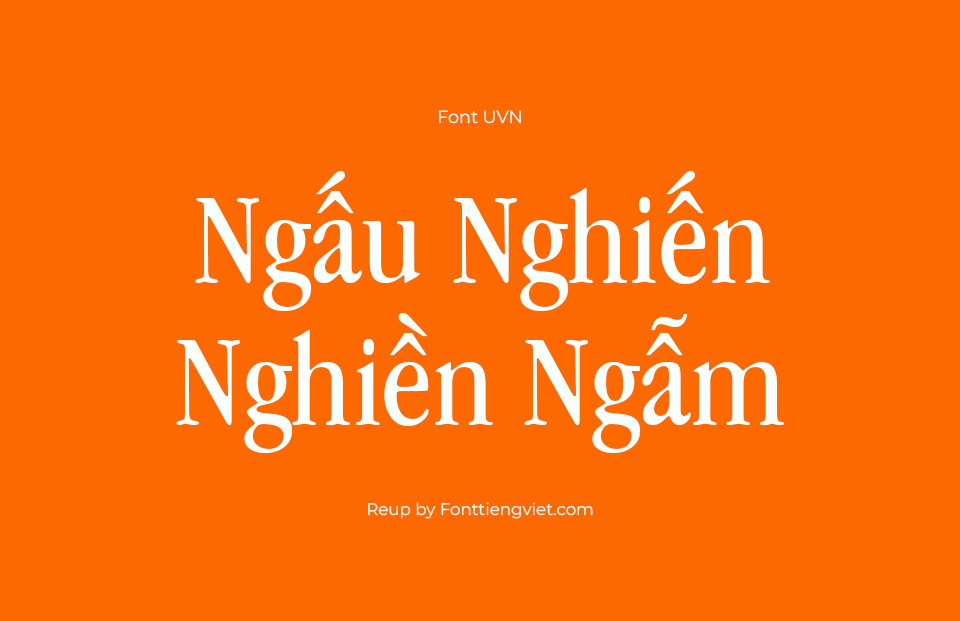
Font Việt Hóa UVN Gia Dinh Hep – Bộ Font Chữ Tuyệt Đẹp Cho Thiết Kế Học Đường
Giới thiệu về Font Việt Hóa UVN Gia Dinh Hep
Trong thế giới đồ họa hiện đại, việc tìm kiếm một bộ Font Chữ phù hợp với văn hóa Việt Nam là điều rất quan trọng. Font Việt Hóa UVN Gia Dinh Hep là một trong những lựa chọn hàng đầu dành cho các bạn học sinh và thầy cô giáo. Đây là phông chữ thuộc bộ UVN nổi tiếng, được tinh chỉnh để hiển thị tiếng Việt một cách hoàn hảo mà không bị lỗi dấu. Với kiểu dáng thanh mảnh và gọn gàng, bộ font này giúp tiết kiệm diện tích trình bày nhưng vẫn giữ được sự tinh tế, trang trọng trong từng nét chữ.
Đặc điểm nổi bật của Font Việt Hóa UVN Gia Dinh Hep
Thiết kế tối ưu cho văn bản dài
Đúng như tên gọi “Gia Dinh Hep”, các ký tự trong bộ font này được thiết kế với chiều ngang hẹp hơn so với các phông chữ truyền thống. Điều này cực kỳ hữu ích khi bạn cần trình bày các đoạn văn bản dài trên báo tường, tờ rơi học tập hoặc các slide thuyết giảng có không gian hạn chế. Font Việt Hóa UVN Gia Dinh Hep giúp nội dung trở nên súc tích, dễ nhìn và không gây cảm giác rối mắt cho người đọc.
Tính ứng dụng cao trong học đường
Phông chữ này mang phong cách cổ điển pha lẫn nét hiện đại, rất phù hợp để làm tiêu đề bài học hoặc trình bày các tài liệu giáo dục. Sự rõ ràng của các nét chữ giúp các em học sinh dễ dàng tiếp nhận thông tin. Hơn nữa, vì đã được Việt hóa hoàn toàn, người dùng có thể yên tâm sử dụng trên mọi phần mềm soạn thảo văn bản hay thiết kế phổ biến hiện nay.